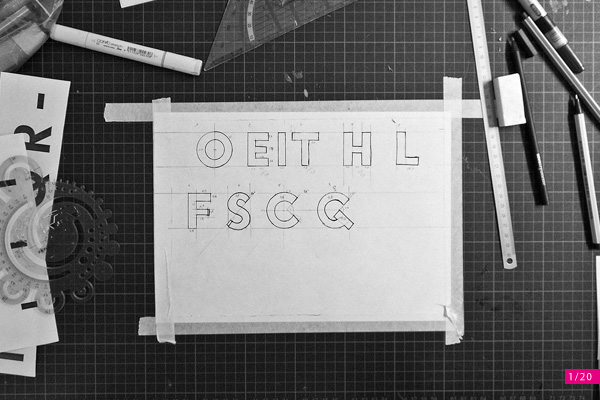
Das Mainzer Grotesk Experiment hinterfragt die Nutzung analogen Satzes im digitalen Zeitalter. In den letzten Jahren kam Handsatz unter Typografen wieder in Mode, ohne der analogen Technik dabei etwas neues abzugewinnen. In einem experimentellem Ansatz wird untersucht, ob die Technik neue Methoden in sich birgt. Um ein möglichst umfassendes Bild von Aufwand und Nutzen zu bekommen, wurde die Mainzer Grotesk von Grund auf neu entworfen, in Blei gegossen und jungen Typografen zum experimentieren im Rahmen eines Workshops zur Verfügung gestellt. Die Ergebnisse des Experiments flossen in das Buch „Das Mainzer Grotesk Experiment“ ein. Konzept und Gestaltung: Zweizehn Design, Fotografie, Konzeption für Kultur & Wissenschaft www.zweizehn.com |